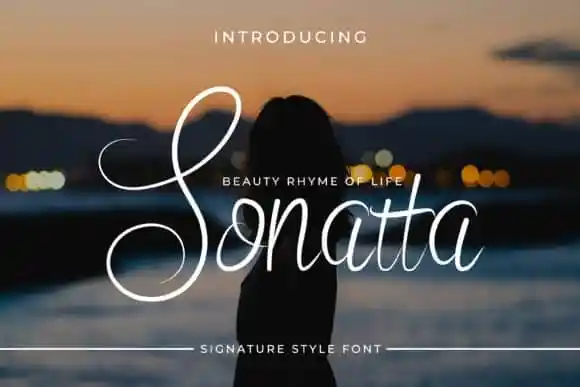
Sonatta Script Font
A Sonatta Script Font é uma elegante escolha para designers gráficos que buscam um estilo descontraído e inspirador para suas criações. Esta fonte à mão-dura criada pelo 99designs é perfeitamente adequada para uso em design de moda, sendo ideal para nomes de marca, logotipos, designs de casamentos, posts nas redes sociais, anúncios, embalagens dos produtos e etiquetas. Além disso, ela também atende bem aos projetos que exigem um estilo de escrita a mão elaborado com destaque, como publicações de fotografias, fundos d’água, convites e materiais de estação. Esse é um recurso indispensável para quem procura uma fonte script para complementar suas ideias criativas em diversas aplicações gráficas.